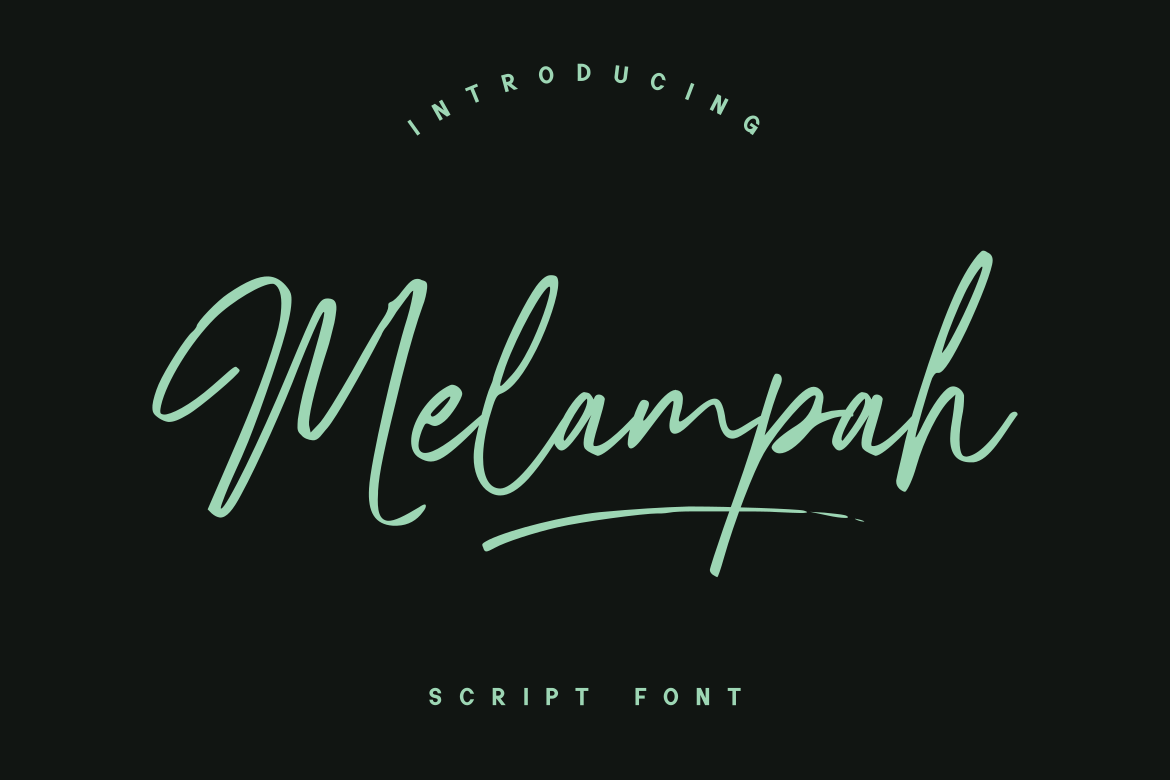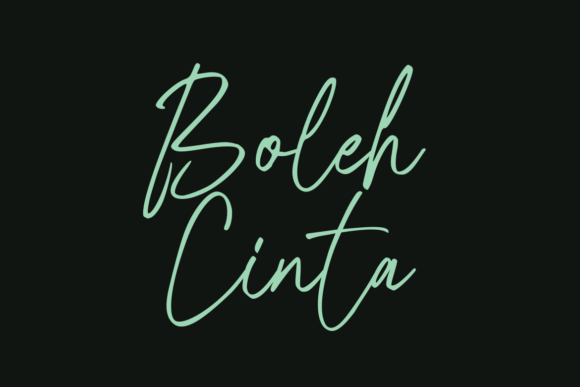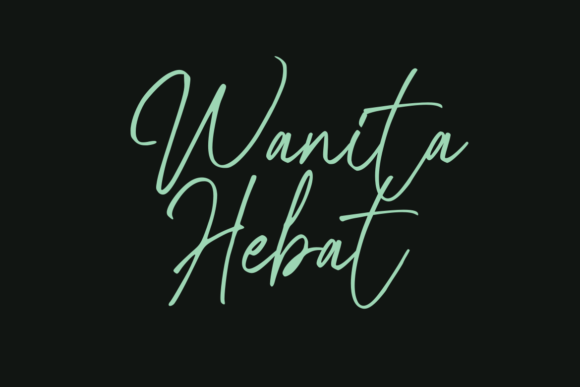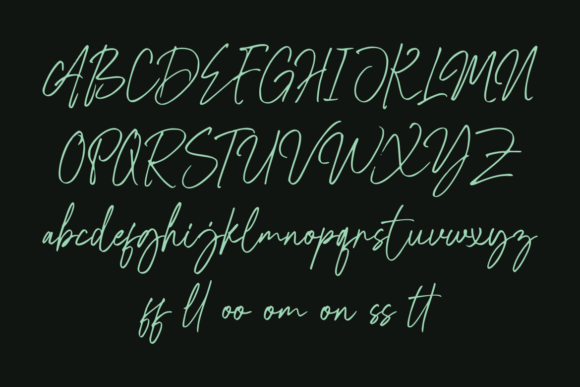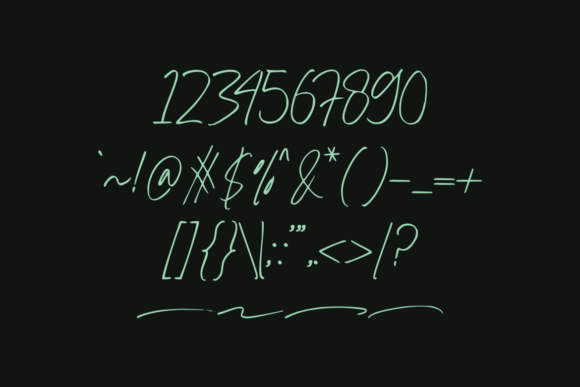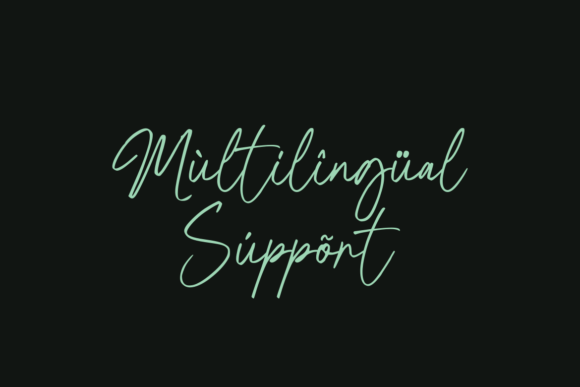
فونت Melampah انگلیسی
دانلود فونت Melampah انگلیسی Font ملامپاه |
| ⭐ مجموعه فونت | دانلود فونت انگلیسی ملامپاه Font Melampah |
| ⭐ توضیحات | فونت ملامپا را معرفی میکنیم، خطی برازنده و روان و حروف دستنویسی که ظرافت و پیچیدگی را میتاباند. این فونت با منحنی های صاف و ضربه های ملایم خود، جوهره زیبایی و ظرافت را به تصویر می کشد.
فونت Melampah که برای دعوتنامهها، مواد برندسازی و طرحهای زنانه ایدهآل است، جذابیتی جاودانه به آن اضافه میکند و حس زیبایی و سبک را با هر حرف القا میکند. |